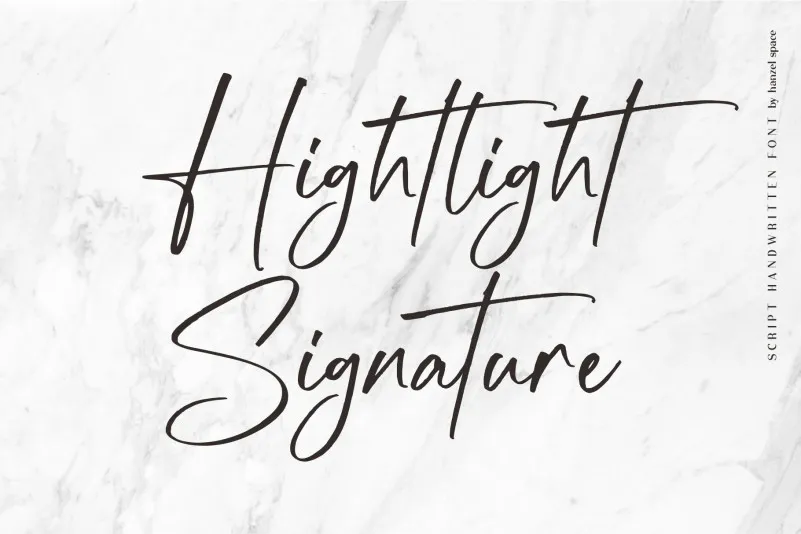
A fonte Hightlight é uma excelente opção para aqueles que buscam uma tipografia script sofisticada, inspirada em uma bela caneta de escritório. Desenvolvida por Hanzel Studio, ela se destaca por sua elegância e facilidade de uso em várias aplicações gráficas, especialmente na criação de marcas de marca, convites para casamentos e cartões. Esta font é perfeitamente adequada não apenas para estilos mais formais e tradicionais, mas também para um toque sofisticado em embalagens de vinho. E sem dúvida, ela encaixa-se como uma pedra filosofal para qualquer projeto que necessite de um estilo elegante e único, oferecendo uma opção versátil e refinada para designers gráficos em todo o Brasil.